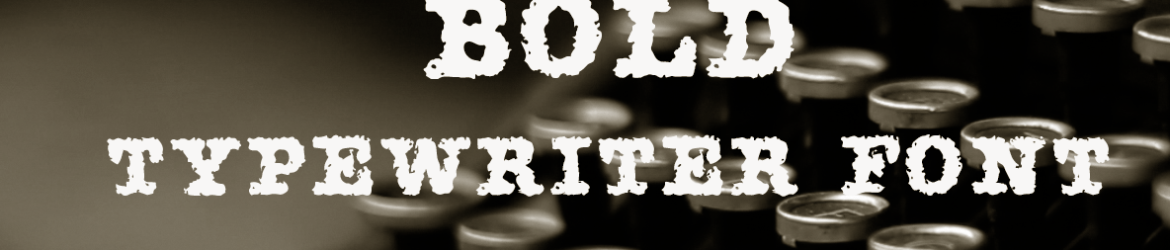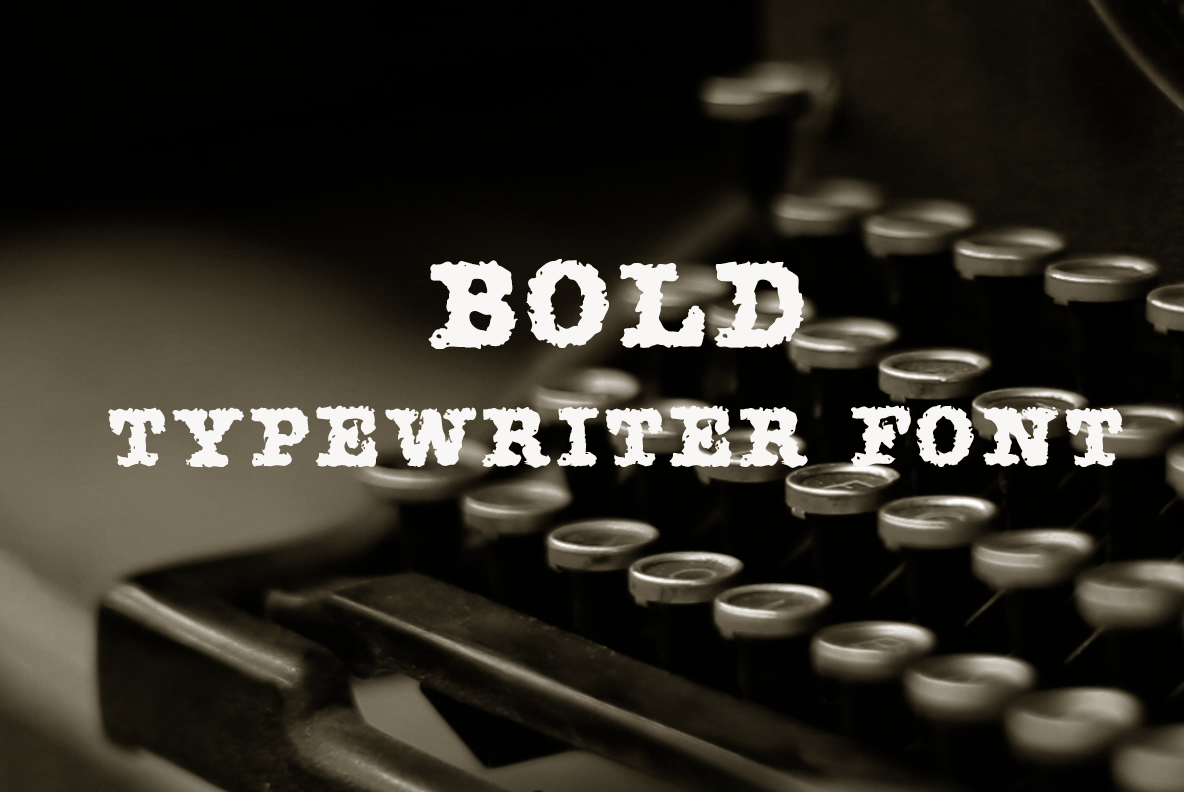
AMTW Typeface – Fonte Grátis
AMTW Typeface
A AMTW Typeface é uma tipografia inspirada nos belos e únicos esquemas manuais dos typewriters, uma vez usados no século XX para escrita rápida e eficiente. Essa fonte vem em todas as suas letras grossas e fortes, oferecendo um estilo único que remete a tempos passados. Ideal tanto para uso pessoal quanto para projetos comerciais, basta entrar em contato conosco  para mais detalhes sobre o uso comercial da AMTW Typeface. Esta fonte é perfeita para designers apaixonados por esse formato nostálgico e versátil.